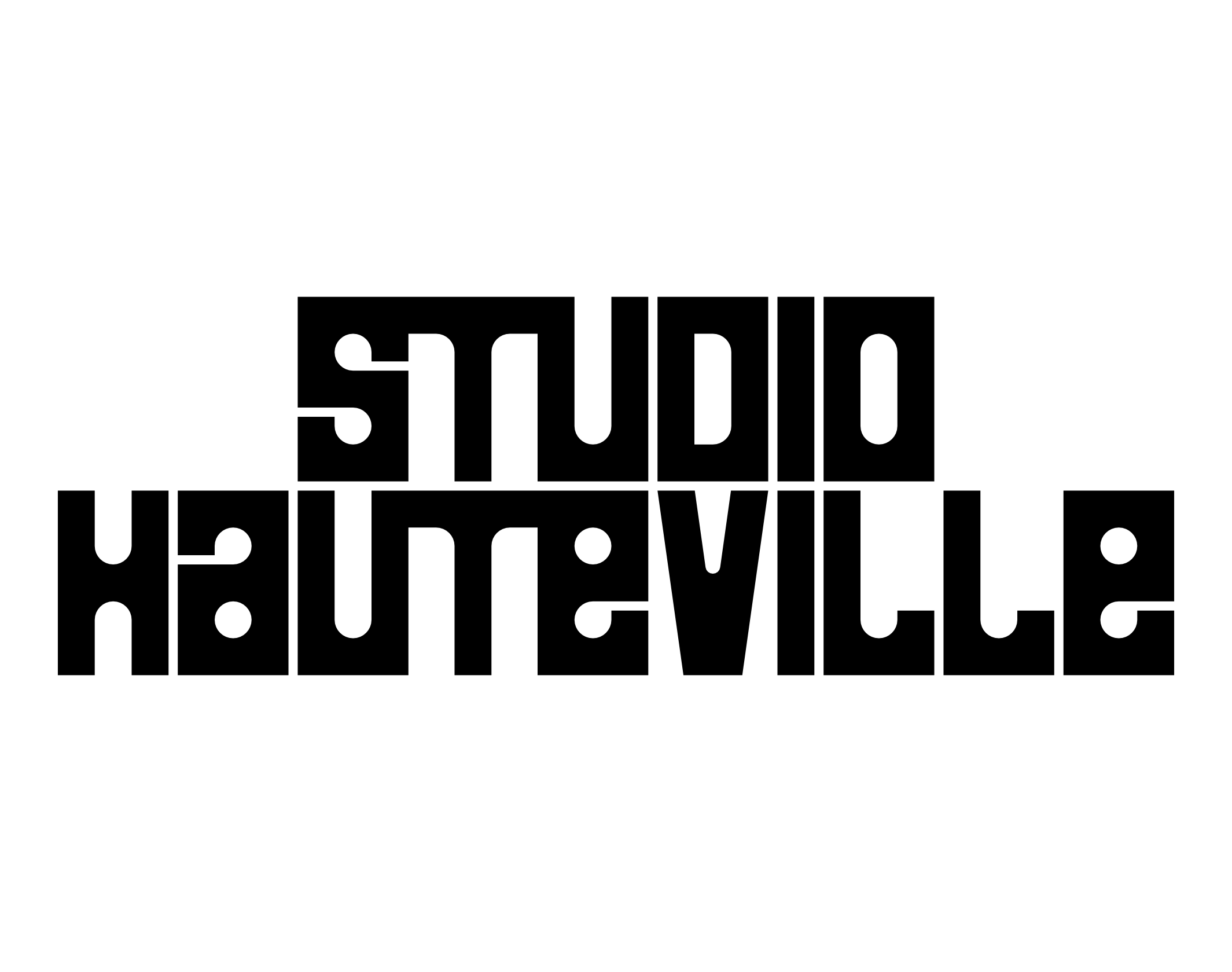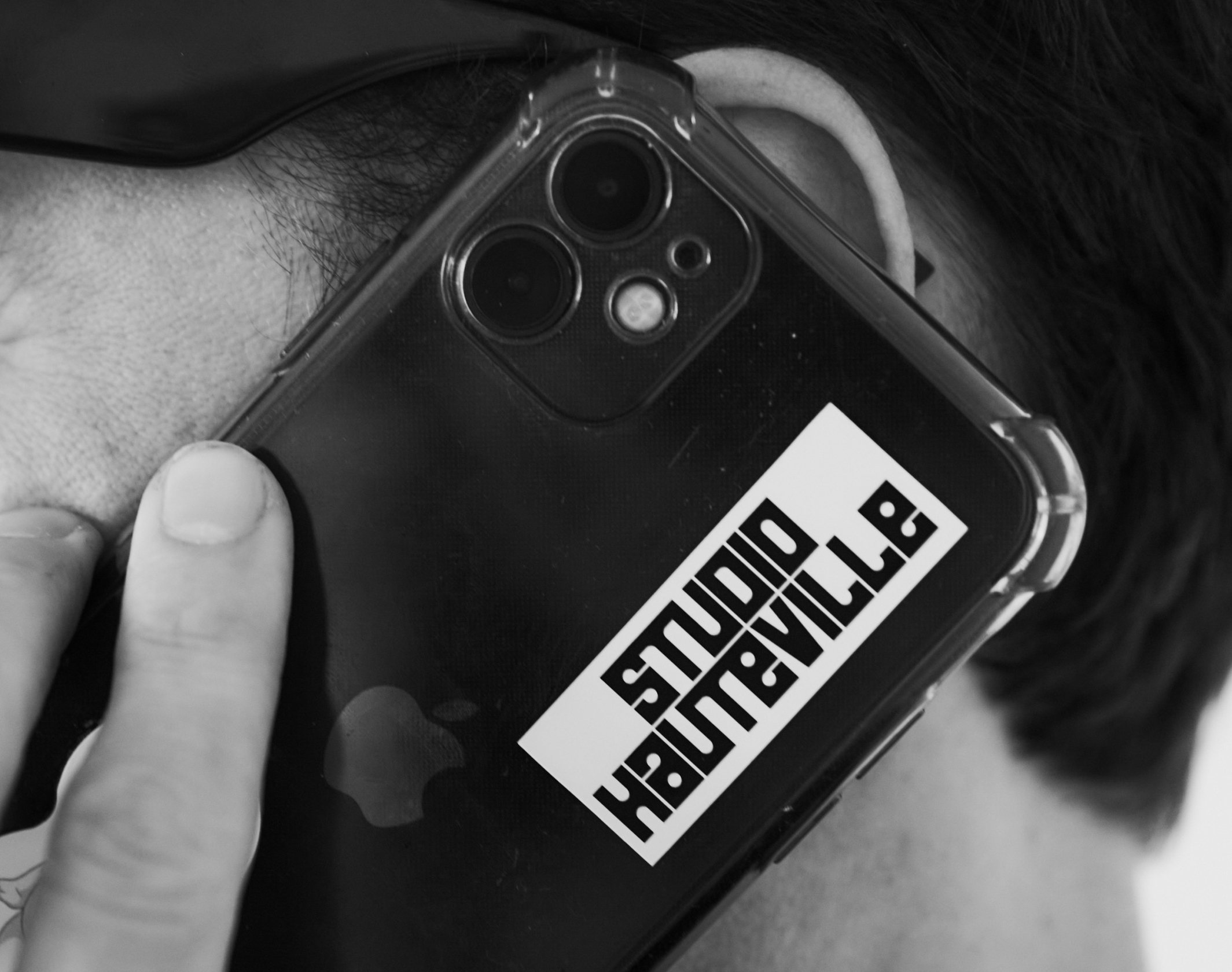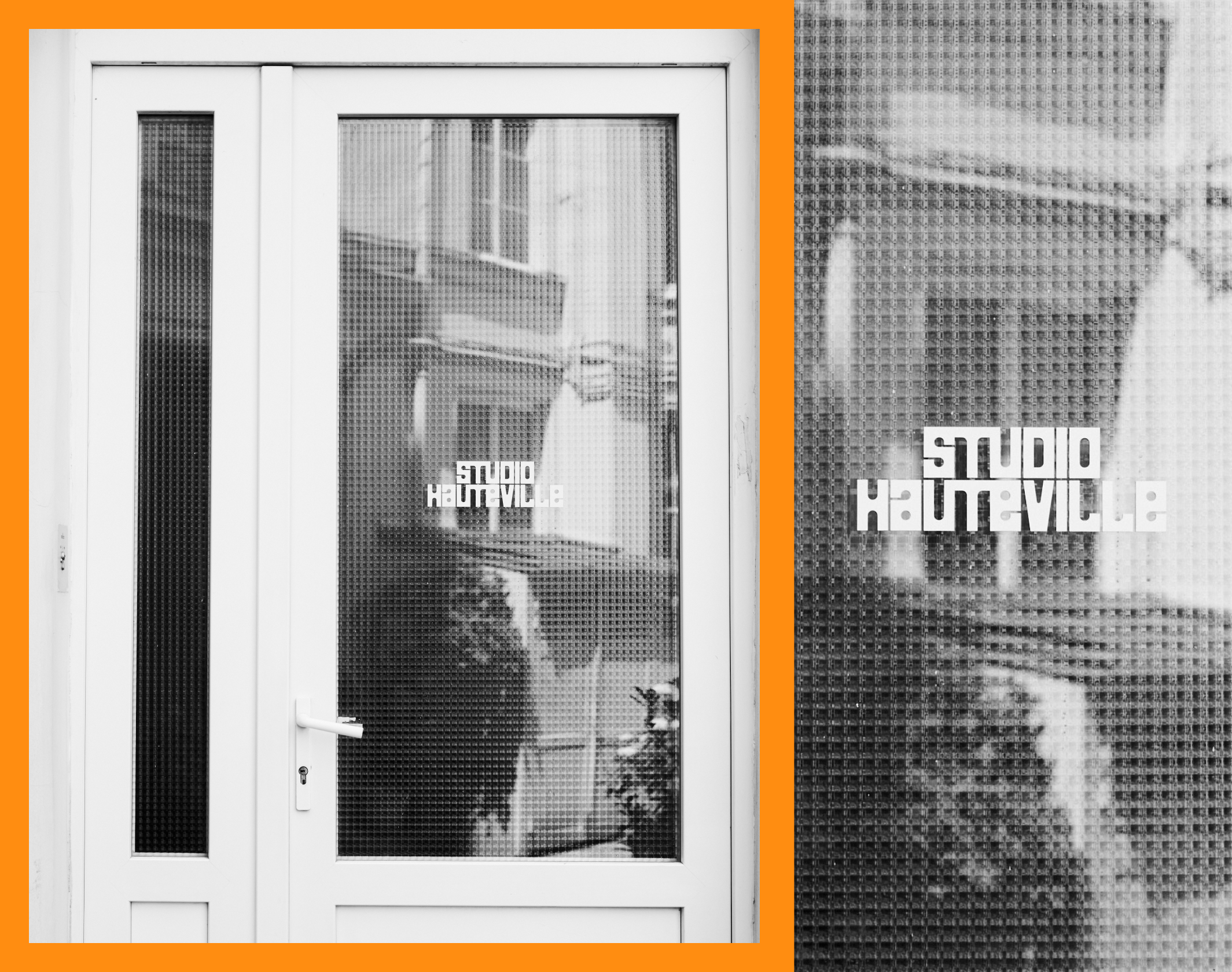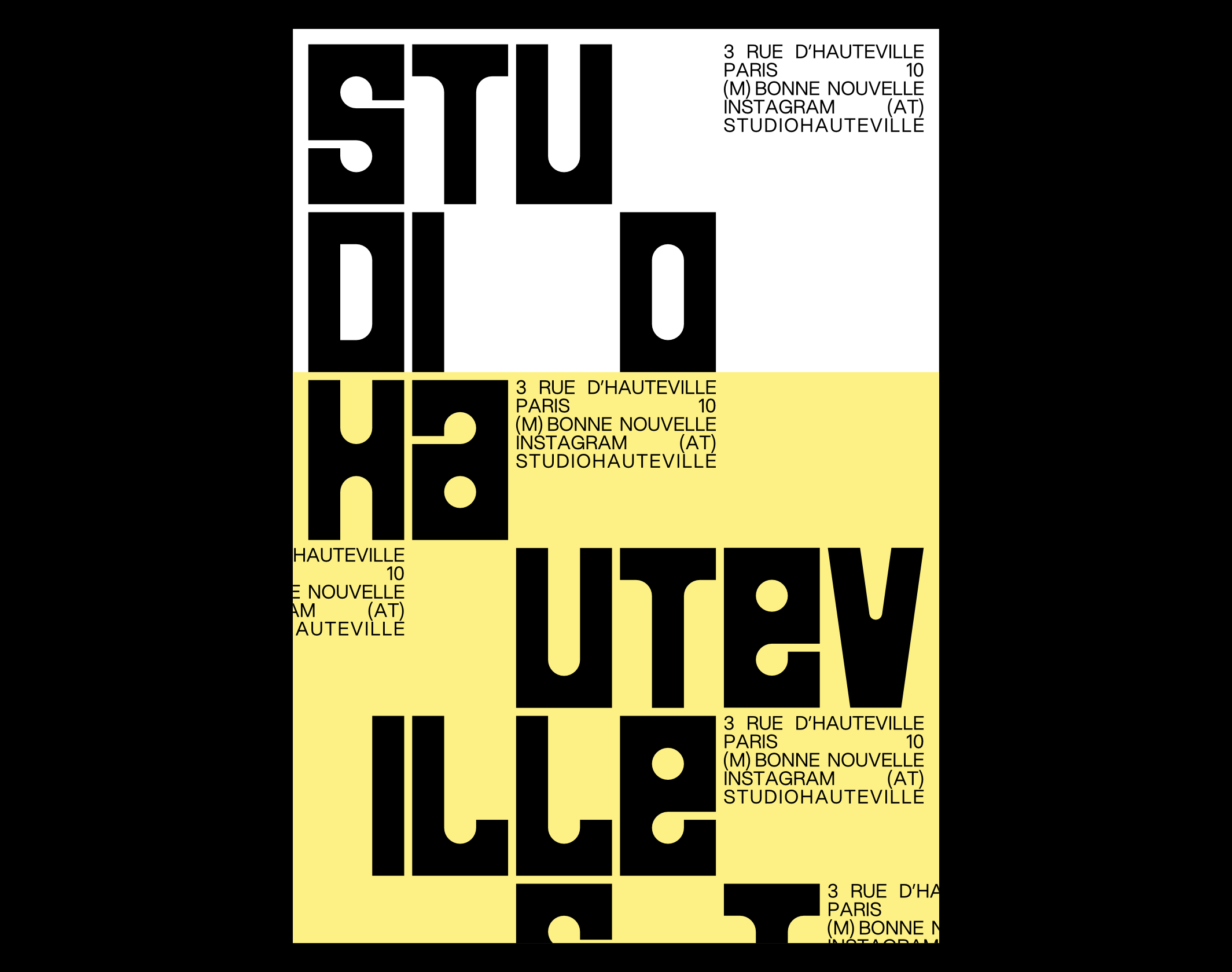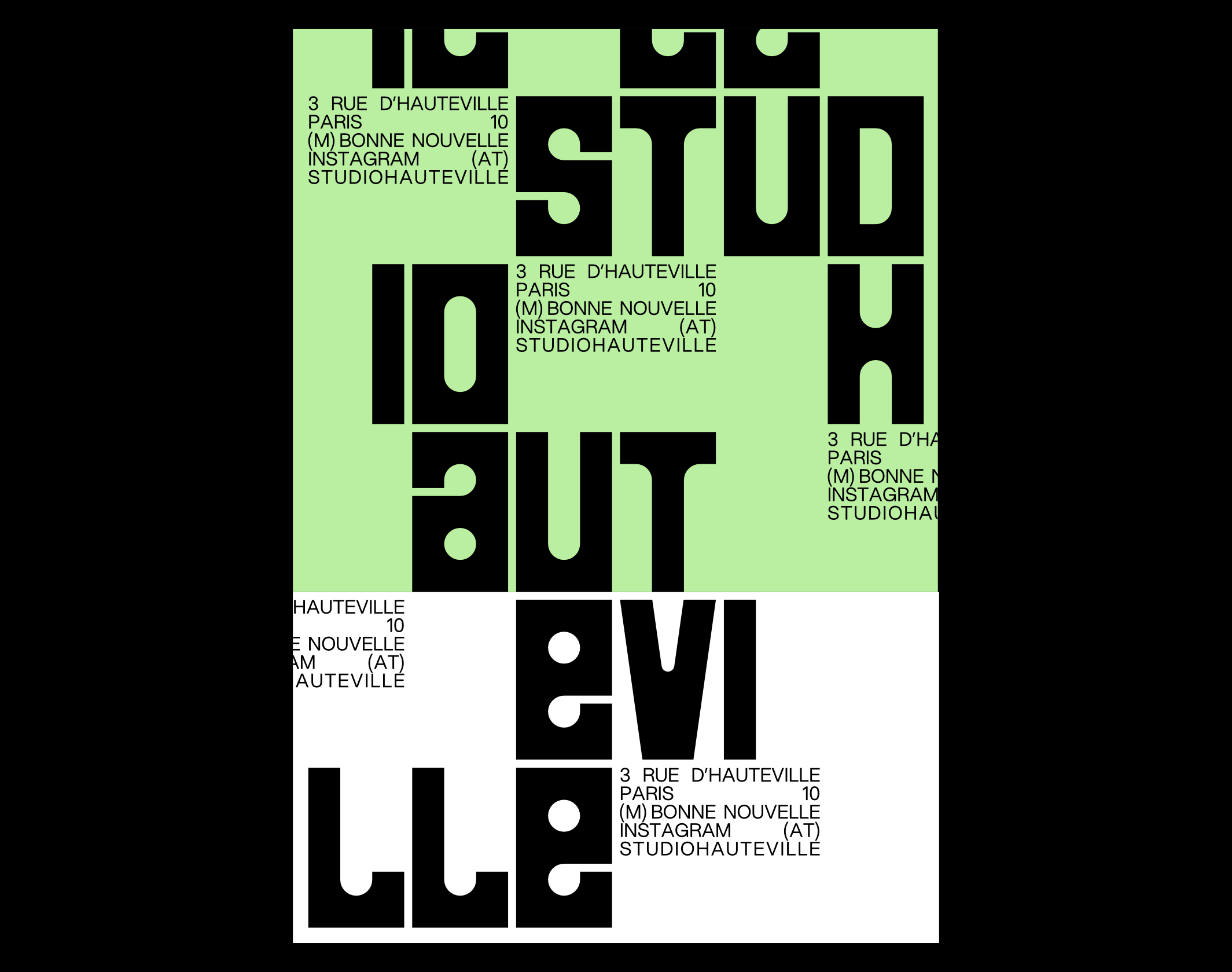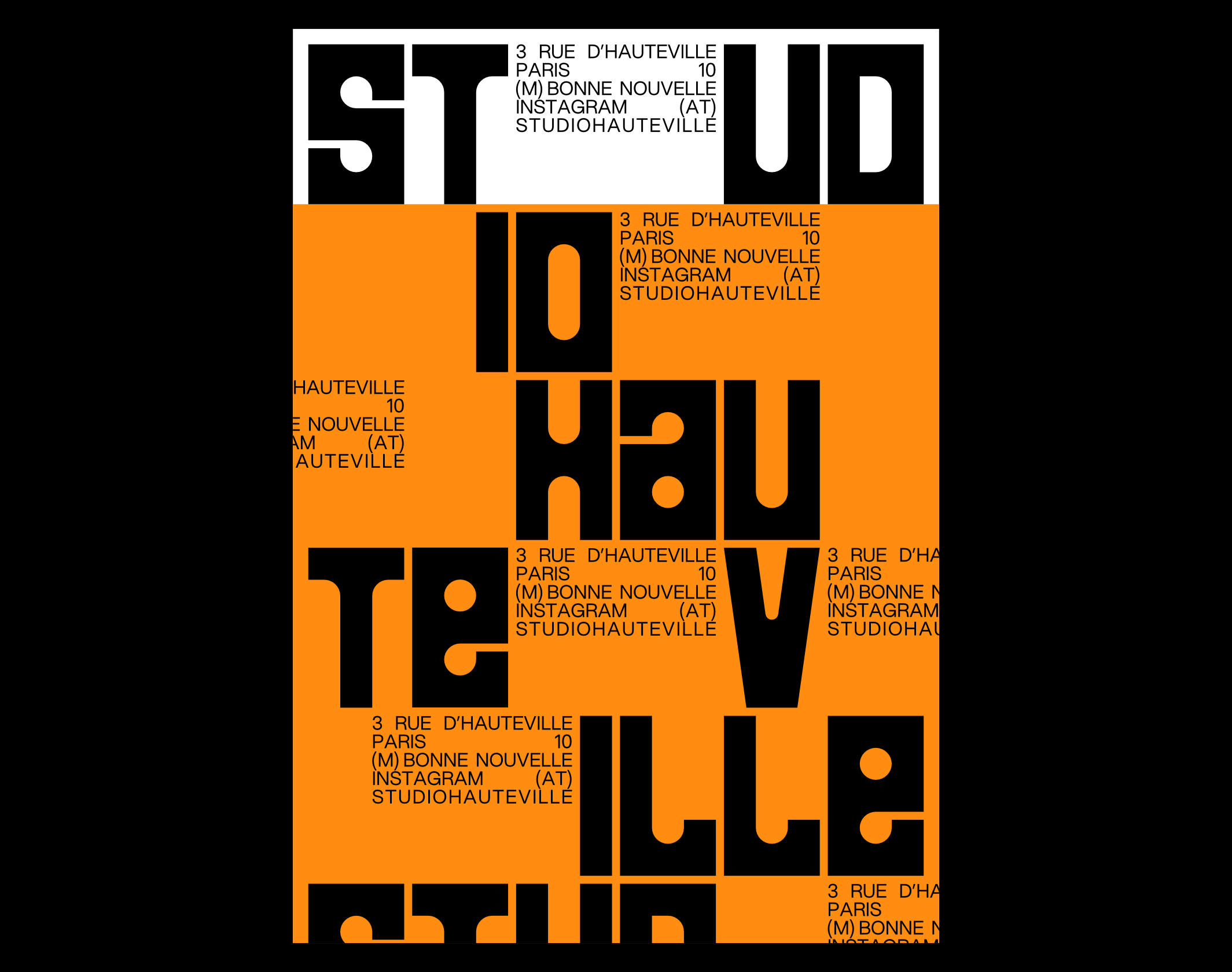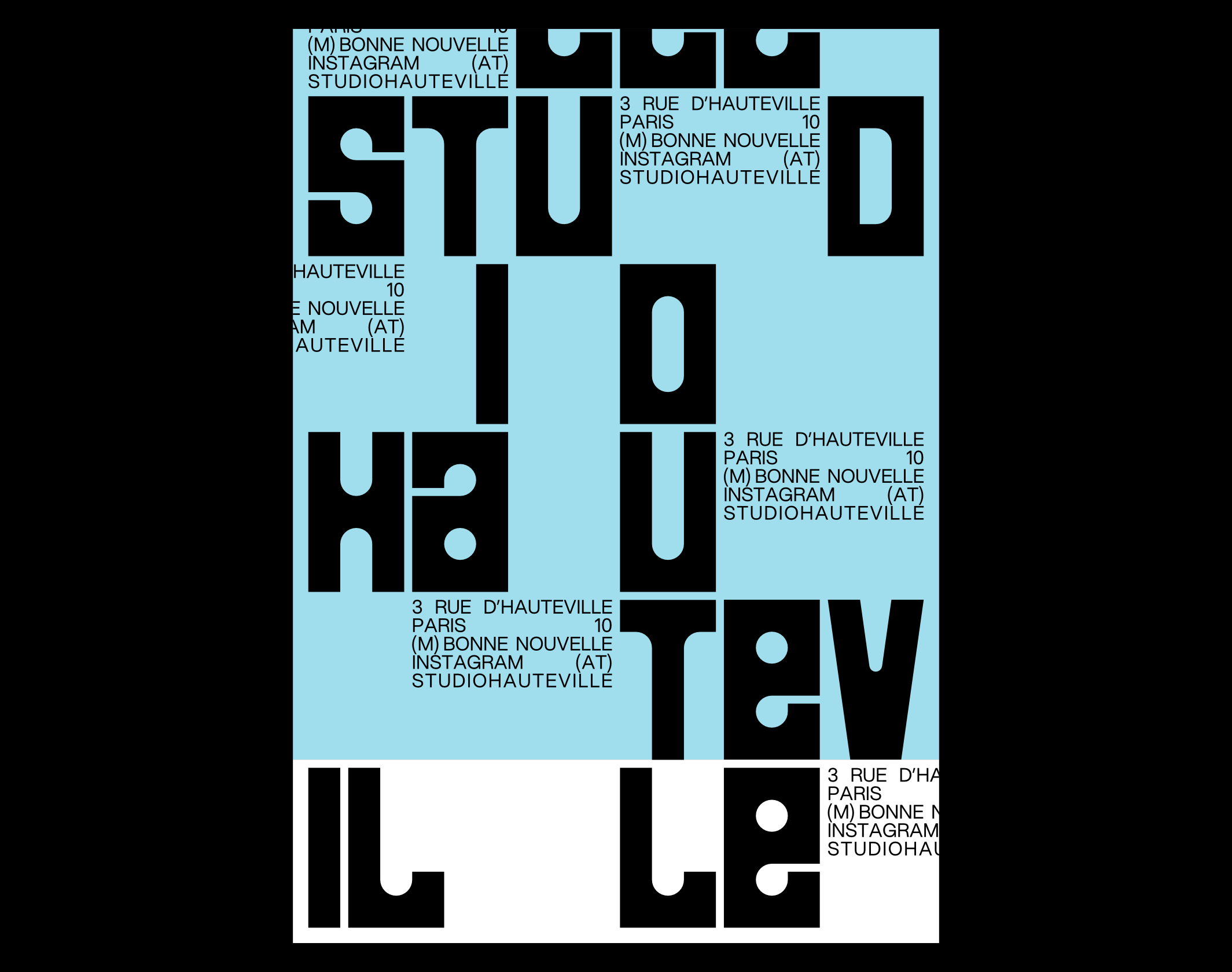
Studio Hauteville
Brand Brothers a créé une identité visuelle charismatique pour le Studio Hauteville, alliant élégance et originalité au cœur de Paris.
Studio Hauteville est un studio photo et vidéo situé au 3 rue d’Hauteville, au coeur de Paris. Il offre sur 160m² des prestations complètes et haut de gamme, dans une ambiance intimiste, à destination des photographes, directeurs de création et producteurs. Brand Brothers a été chargé d’en imaginer l’identité visuelle en vue de l’inauguration du studio qui a eu lieu au printemps 2023.
Notre proposition est axée sur un typogramme doté d’une structure logique et organisée, mais ponctué d’accidents graphiques qui lui confèrent un caractère à la fois charismatique et accueillant. Cette identité prend vie sur de multiples supports, dont une série d’affiches graphiques qui viennent enrichir l’agencement intérieur du studio.